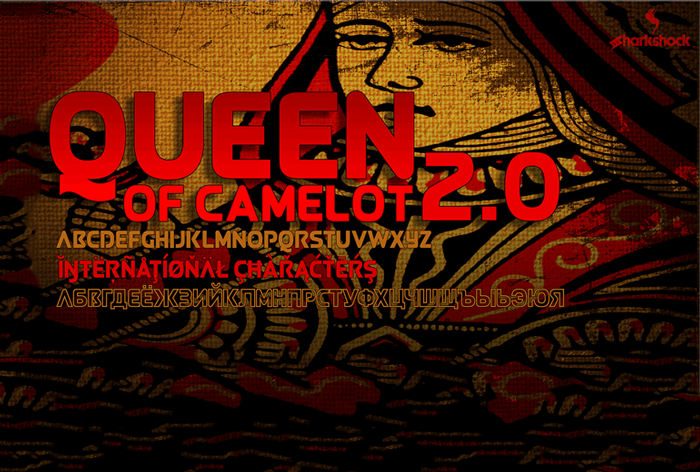
Queen of Camelot 2.0 Font – Download Grátis
Nossa fonte ‘Queen of Camelot 2.0’ é uma elegante escolha para qualquer projeto que deseja trazer dinamismo e modernidade ao seu design. Com seu estilo de sans-serif, essa nova versão de 2017 oferece os três formatos principais: Regular, Italic e Outlines, criando um visual rico em variedade e personalização. Ela é perfeita para uso em sites profissionais, materiais gráficos digitais ou até mesmo design impresso, proporcionando um toque de leveza sem perder a sua força expressiva. Para os designers que desejam adicionar um toque mais marcante, as opções Outlines são uma escolha ideal. Este formato é especialmente útil para destacar letras individuais em elementos gráficos ou quando se quer dar destaque ao texto. Em resumo, ‘Queen of Camelot 2.0’ é uma fonte que traz um toque moderno e inovador à sua criação, feita especialmente para designers que valorizam a simplicidade e o equilíbrio na estética visual.